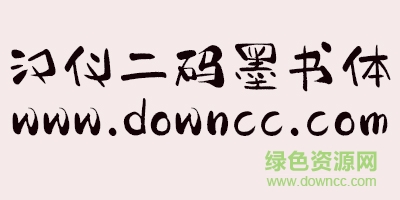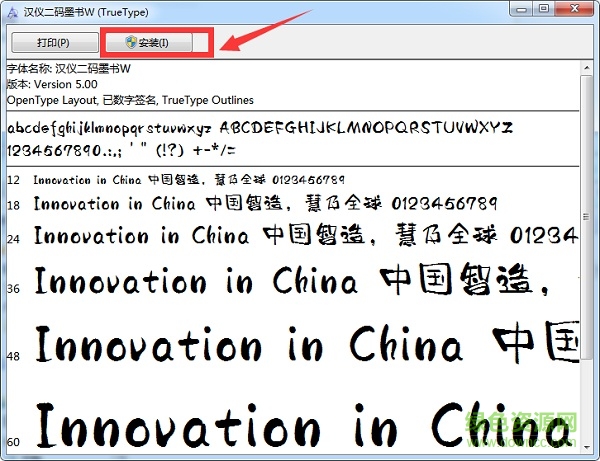
漢儀二碼墨書(shū)字體是一個(gè)免費(fèi)的字體文件。小編為大家提供的這款漢儀二碼墨書(shū)體為簡(jiǎn)體版,輸出的文件非常美觀,用來(lái)做設(shè)計(jì)再好不過(guò)了!歡迎大家下載使用。
漢儀二碼墨書(shū)體能夠應(yīng)用于文本裝潢、信息展示、篆刻制模、數(shù)據(jù)制作、網(wǎng)頁(yè)設(shè)計(jì)、裝潢設(shè)計(jì)、計(jì)算藝術(shù)設(shè)計(jì)、視覺(jué)設(shè)計(jì)、字帖等一切合法應(yīng)用場(chǎng)景。